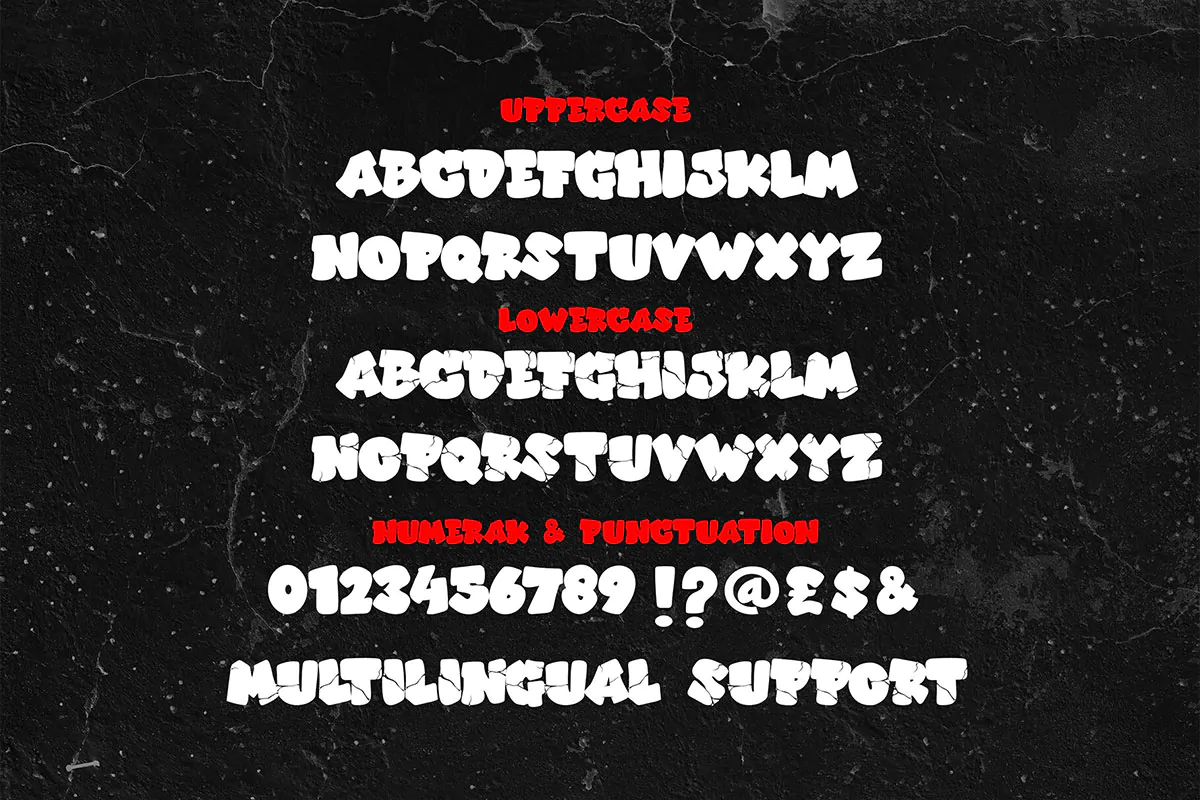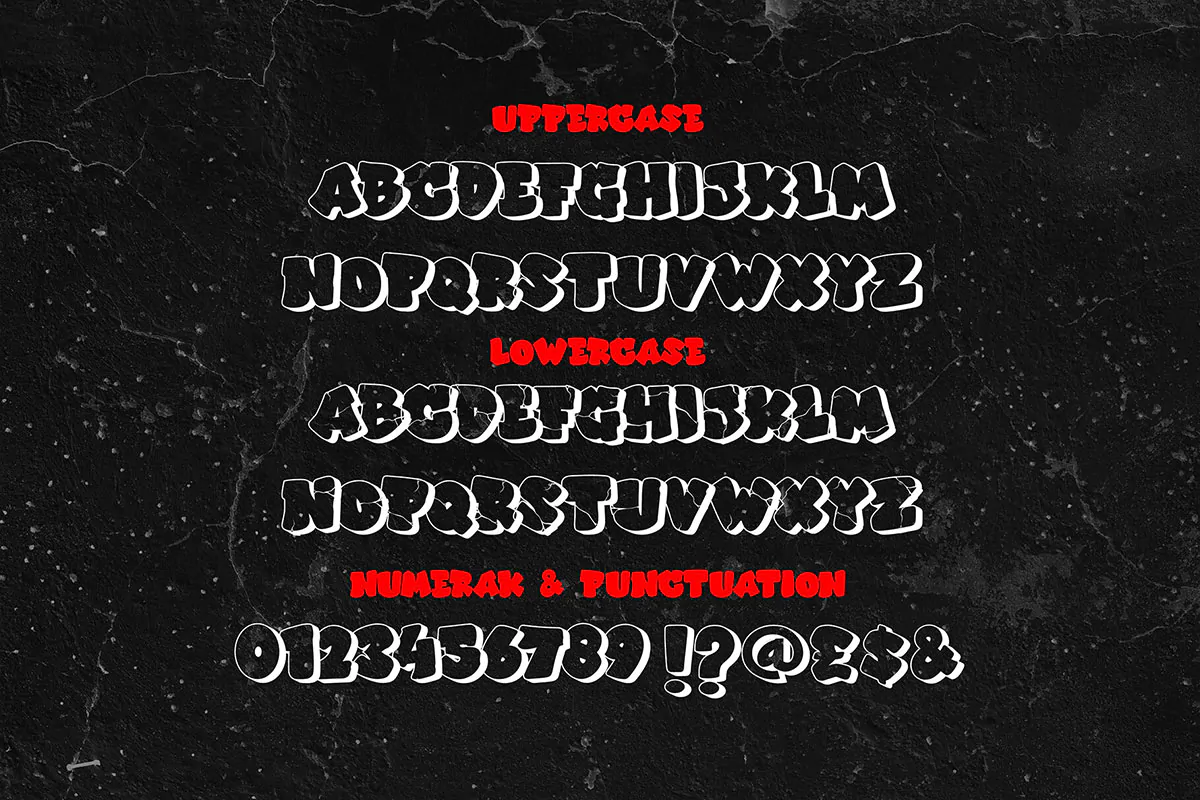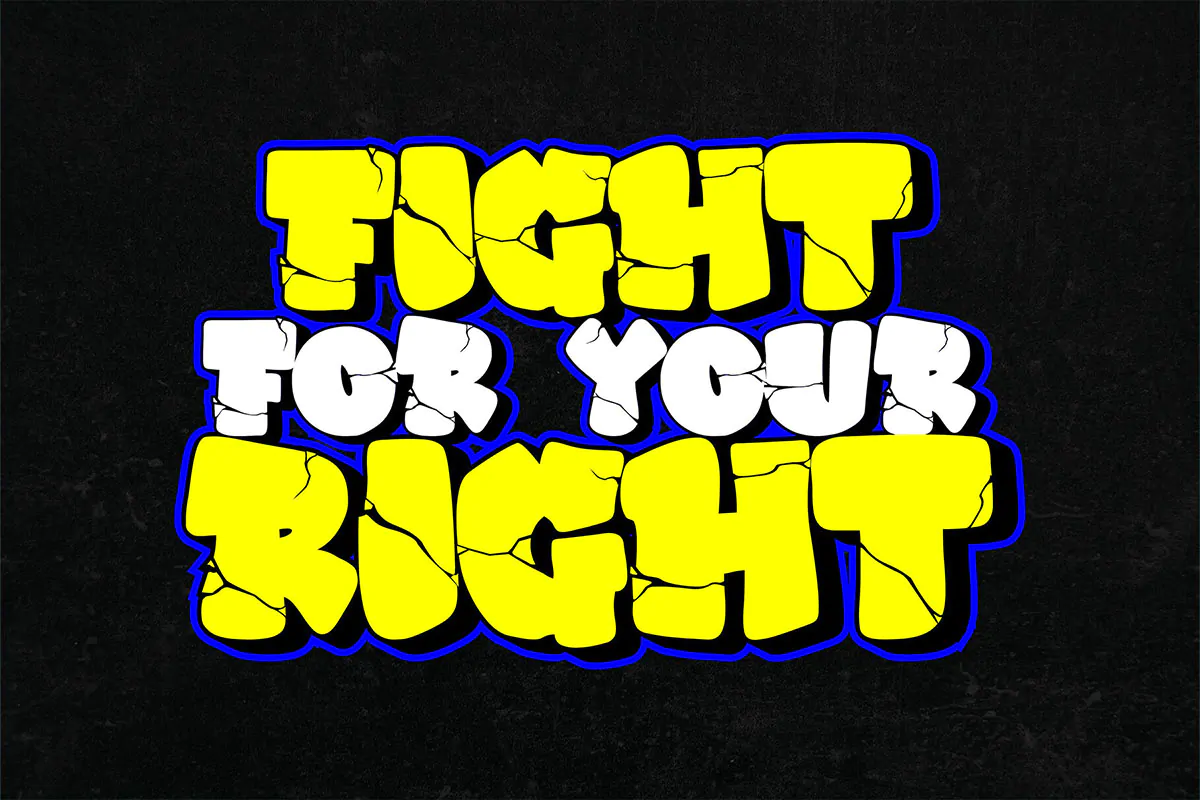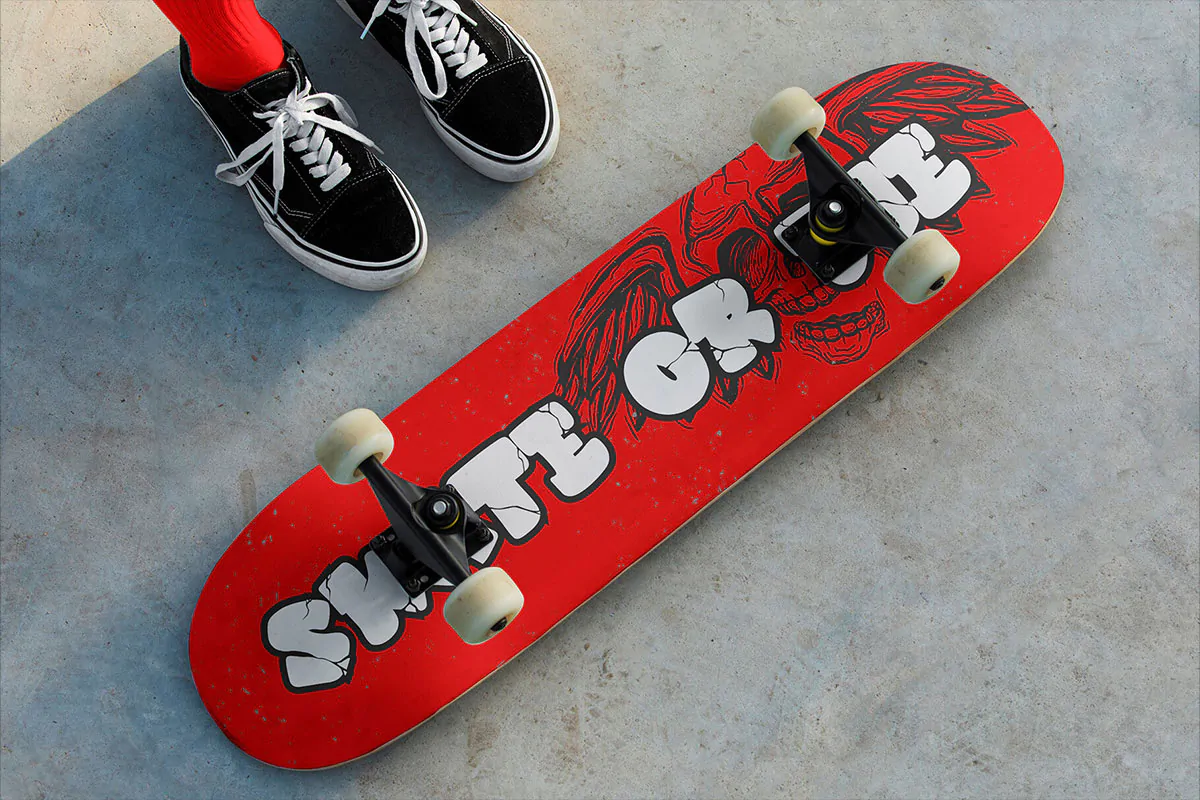
فونت دیوارنگاری Vandal Soul
فونت دیوارنگاری
فونت دیوارنگاری Vandal Soul یک قلم فوق العاده زیبای انگلیسی است که میتوانید از آن در طرح و پروژههای گرافیکی مختلف به خصوص طراحی انواع پوستر استفاده کنید.